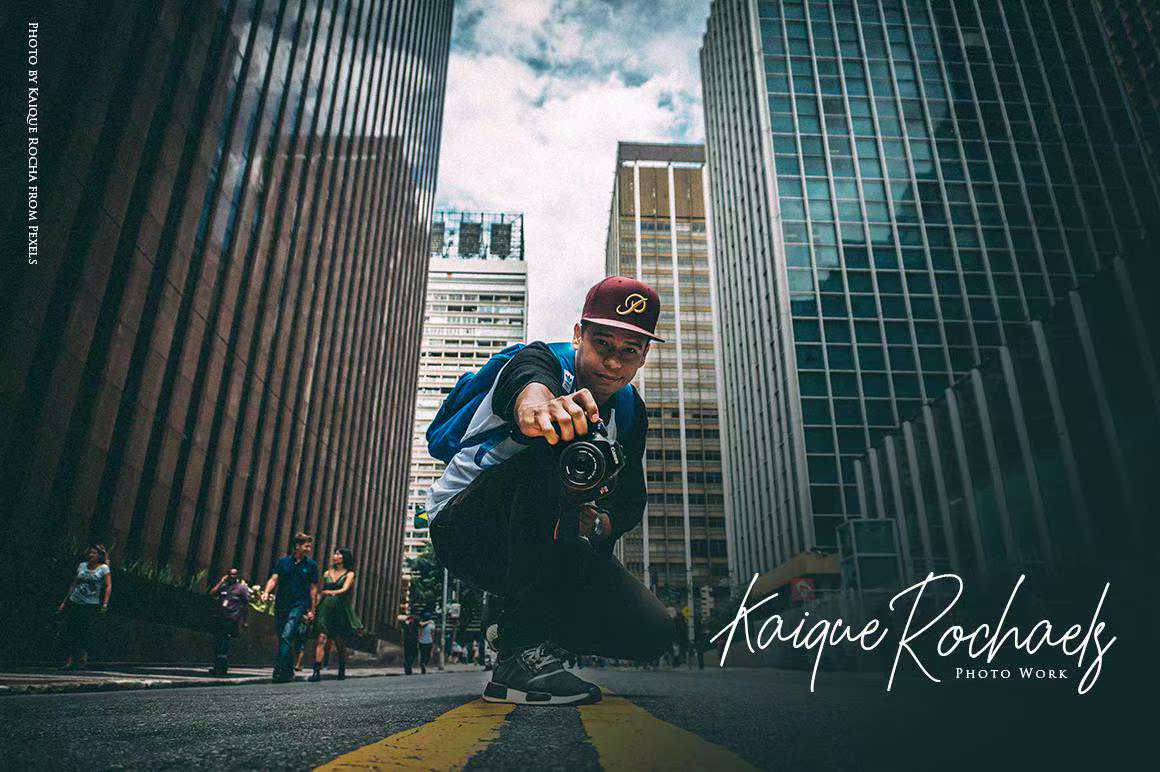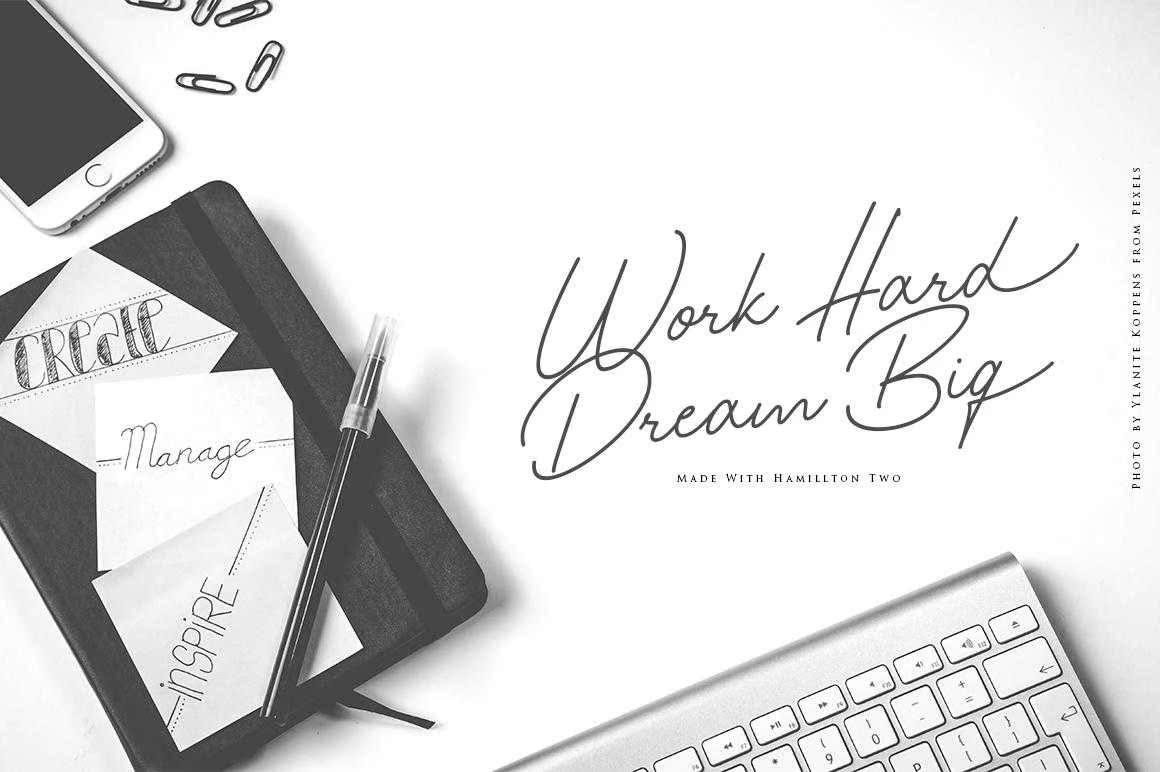
这是一款简单而精致的手写字体,哈密顿为您的房子设计了3种不同的字体,每种不同的字体都有不同的字体,配备了可供选择的开放式字体特征、首字母和最终字母、连字。我们让这款字体看起来优雅、优雅、易读、时尚、难忘且简单。哈密顿是Arkson摄影的完美选择,Logo Designer或签名、报价、专辑封面、名片和其他许多设计项目。从名片Stop Hot Watermarks,Hamill To到您的设计,Hamill To可以重复和删除。这是Hamill Ton通过简单的删除手写,Hamill To为您的房屋提供了3种变体,每种变体为您的房屋提供不同的类型,配备了可选的OpenType功能,首字母和最终形式、连字。我们保持此字体的优雅、优雅、易读、时尚、难忘和简单。Hamillton是摄影、标志设计或签名、报价、专辑封面、名片和其他许多设计项目的完美选择。从名片StopHotoWatermarks开始,Hamill将介绍您的设计。